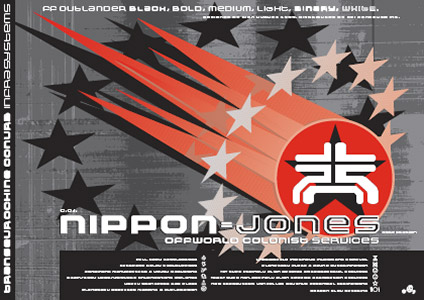
Sammelkarte: Techno-Font OutlanderIm Januar 1995 erschien die Techno-Schriftfamilie FF Outlander, entworfen
von Rian Hughes. Der Comic-Künstler und Schriftentwerfer aus London schuf
eine futuristisch gestaltete FontCard zu seiner Neuerscheinung, in deren